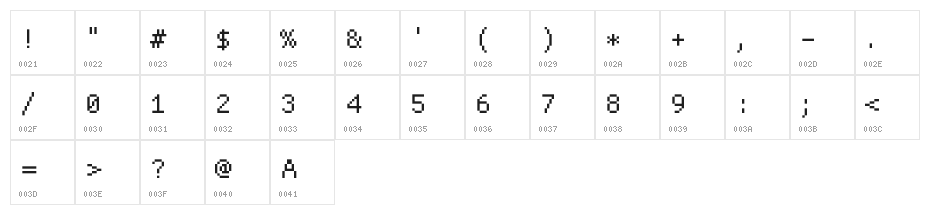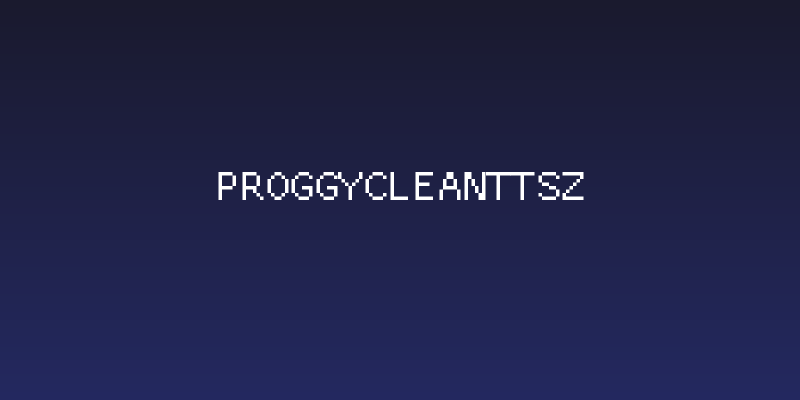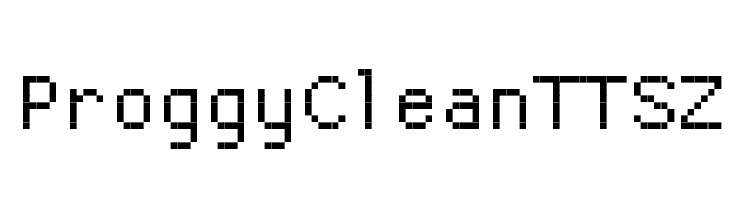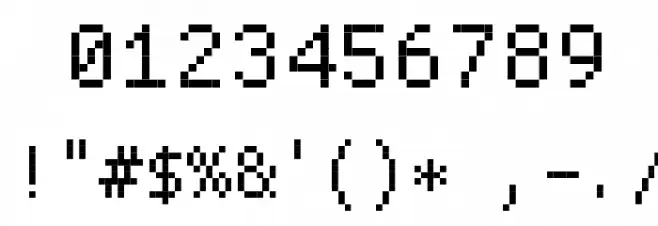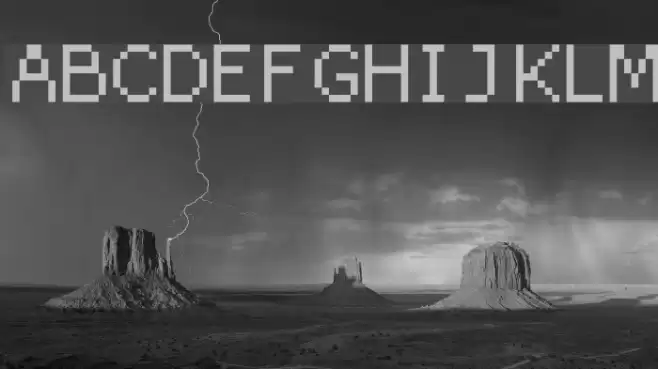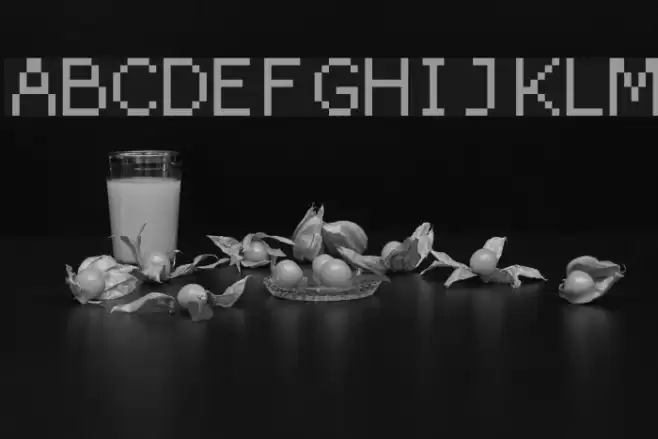
ProggyCleanTTSZ Font
✎ Pixel
| Catégories | Pixel |
| Espacement des caractères | Normal |
| Style général | Retro |
| Cas d'utilisation | Coding, Digital Art, Retro Designs |
| Projets proposés | Perfect for coding editors, retro video game graphics, digital art projects, and any design requiring a vintage computer aesthetic. |
| Est-hélice à pas fixe | Yes |